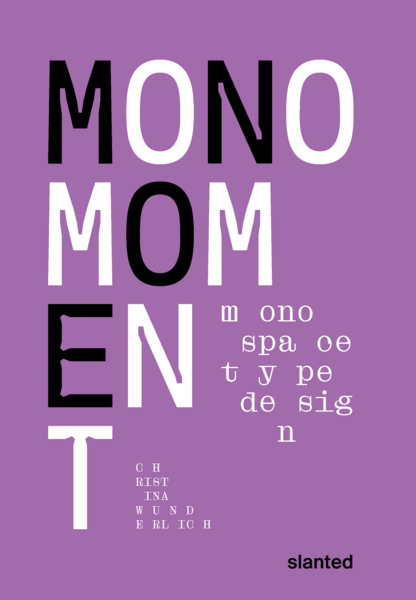
Monospaced-Schriften zeichnen sich durch ihre feste, gleiche Breite für alle Zeichen aus. Jedes Zeichen, jeder Buchstabe und jede Zahl nimmt horizontal und vertikal den gleichen Platz ein. Proportionale Schriften hingegen haben harmonisch ausgewogene Abstände mit variablen Breiten zwischen den Zeichen. Die Abstände sind nicht proportional festgelegt. Aus diesem Grund werden einzeilige Schriften auch als nichtproportional bezeichnet. Durch die Zunahme der Schriftproduktion in den letzten Jahrzehnten hat fast jede gut entwickelte Schriftfamilie auch einen Mono- oder Semi-Mono-Schnitt. Wenn man im World Wide Web nach dem Wort »Monospace« sucht, findet man neben den Ergebnissen wie »Ich suche eine schöne Monospaced-Schrift«, »Top Ten Monospace Fonts« oder »Best Monospace Fonts for Coding« unzählige Einträge. In einer Zeit, in der es noch nie so einfach war, Schriften zu entwerfen und zu veröffentlichen, bietet dieses Buch eine Orientierung zum Thema Monospace.
Vorgestellte Schriftarten: Airport Mono, Andal Mono, Anonymus Pro, AO Mono, Aperçu Mono, Atlas Typewriter, Base Mono, Basier Mono, Blue Mono, Calico Mono, Cindie D, Consolas, Courier, Cygnito Mono, Eureka Mono, GT Pressura Mono, IBM Plex Mono, Input Mono, Kettler, Letter Gothic, LTC Remington, Maison Mono, Monaco, Monoela, MonoLisa, Orator, Pica 10 Pitch, Pitch, Plastic, Platelet, Roboto Mono, Simon Mono Light, Sneak Mono, Source Code Pro, Space Mono, Splendid 66, Sudo, Suisse Int'l Mono, SYNO MONO, The Future Mono, TheSans Mono, Typist Code, Typist Slab, Ubuntu Mono, and Vulf Mono.
Design: Christina Wunderlich
Schriften: Droulers, Monument Grotesk Regular / Italic, Monument Grotesk Mono, Monument Grotesk Semi-Mono
Untertitel: Mono Space Type Design
Autor(en): Christina Wunderlich